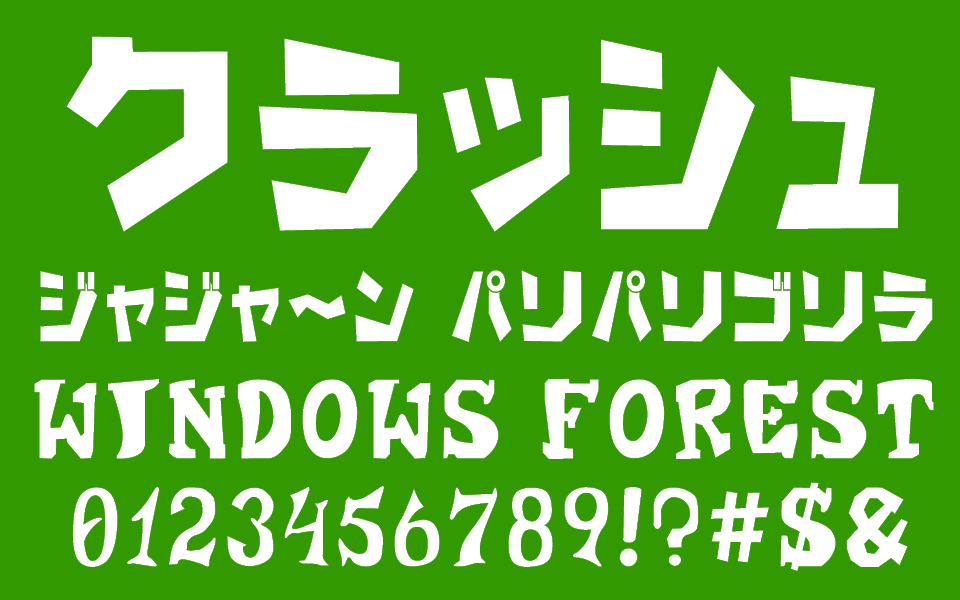
クラッシュ・バンディクーの文字を復刻した「クラッシュふうフォント」
20周年を記念した非公式作品、助っ人キャラ“アクアク”の台詞が蘇る
「クラッシュふうフォント」は、人気ゲームシリーズ『クラッシュ・バンディクー』の文字を再現するフォント。ひらがな、カタカナに加えて、大文字のアルファベット、2種類の数字、一部の記号を収録。
1作目が1996年12月6日に発売された『クラッシュ・バンディクー』は今年でちょうど20周年を迎え、先月開催のE3(Electronic Entertainment Expo)にてPS4向けリマスター版の開発が発表された。「クラッシュふうフォント」もその20周年を非公式に記念している。
角張った大胆なデザインは、アメリカのドタバタ劇“カートゥーン”を思わせ、『クラッシュ・バンディクー』のユルくコミカルな雰囲気をそのまま反映したかのよう。ゲーム内に登場する助っ人キャラ“アクアク”が話す台詞や、英字のエンドロールが蘇る。